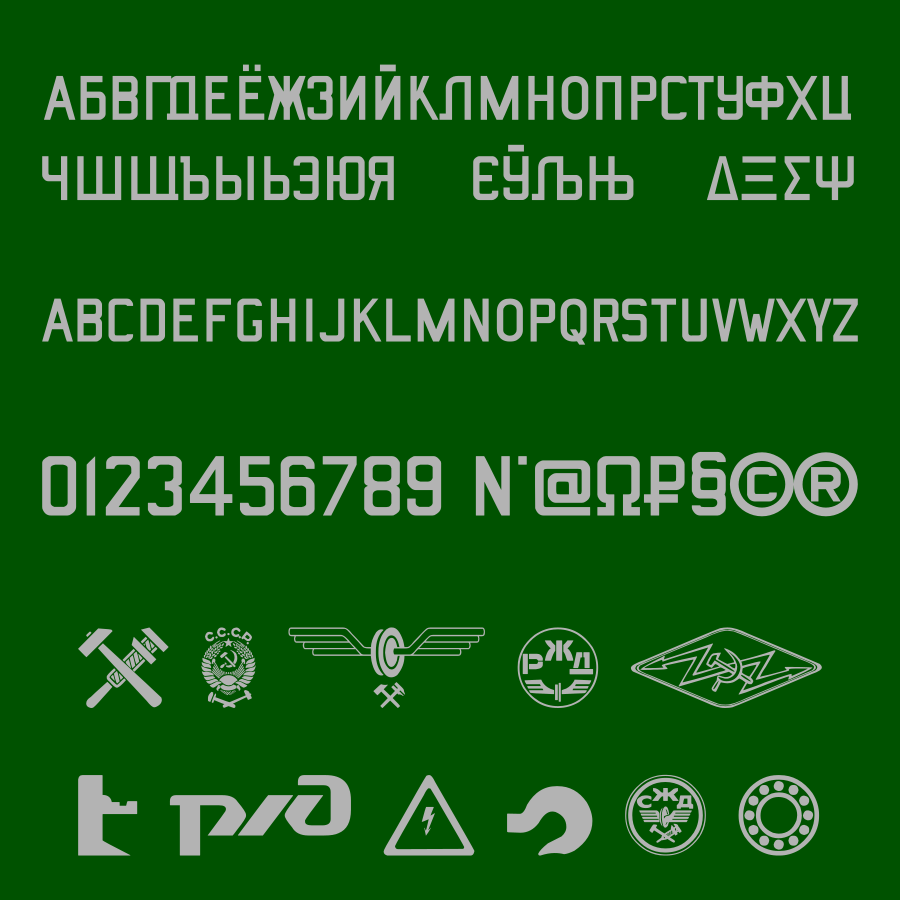
Железнодорожный шрифт⁠⁠
Друзья, предлагаю новую версию своего бесплатного шрифта RailwayCargoRus2022.
Шрифт  повторяет начертание надписей на грузовых железнодорожных вагонах.
Шрифт включает в себя полную кириллицу, базовую латиницу и греческий алфавит.
Кроме буквенных знаков есть знаки препинания, специализированные символы, а самое любопытное — железнодорожные пиктограммы и эмблемы.
Версии шрифта отличаются начертанием цифр.
Основа для разработки шрифта: альбом-справочник 632-2011 ПКБ ЦВ «Знаки и надписи на вагонах грузового парка железных дорог колеи 1520 мм».
В соответствии с материалами альбома строчные буквы не отличаются от прописных.
Заметен ряд ошибок. Возможно, ТС литеры брал откуда-то, но их всё ж следовало бы адаптировать.